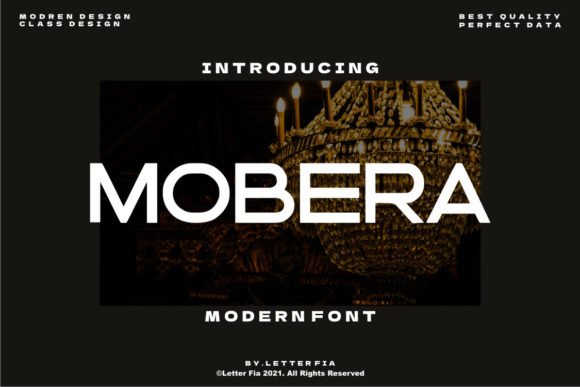
[Creativefabrica] Mobera Font (2021)
Mobera - это смелый и аутентичный шрифт sans serif.
Его можно легко подобрать к невероятно большому набору проектов, поэтому добавьте его в свои творческие идеи и обратите внимание, как он выделяет их!